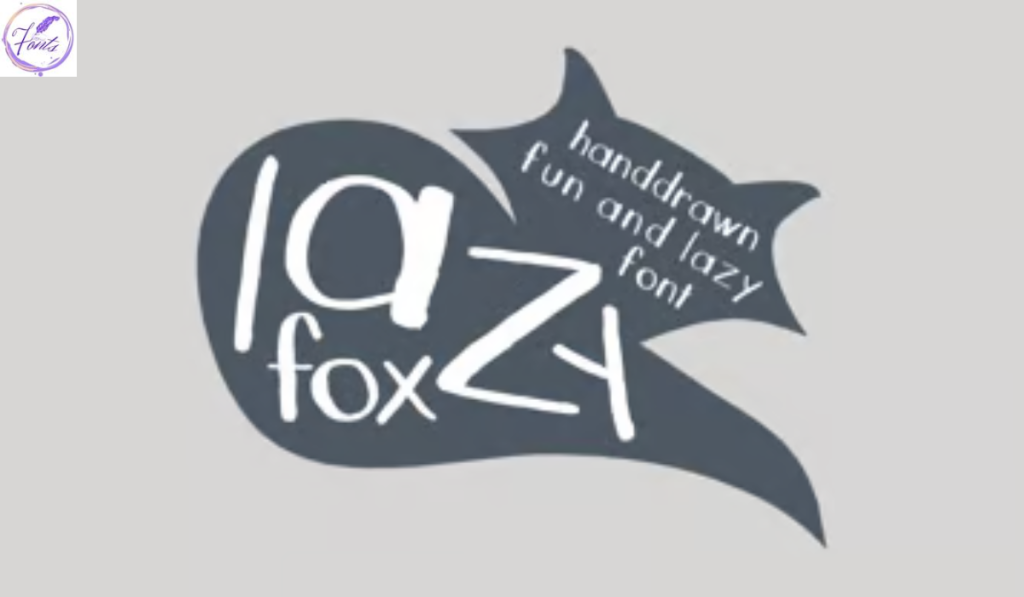
Font The Lazy Fox việt hóa
Tác giả: Jen Wicker
Ngày phát hành: 2019
Bộ Font: Lazy Fox
Phân loại: Cá tính, độc đáo
Kiểu chữ: Viết tay (handwritten)
Font The Lazy Fox là một kiểu chữ độc đáo và thú vị, ra mắt vào năm 2019 bởi Jen Wicker. Với những nét chữ mềm mại, thân thiện, và một chút nghịch ngợm, font the lazy fox mang đến cảm giác tươi mới và vui nhộn cho bất kỳ dự án thiết kế nào. Font này rất phù hợp cho các thiết kế thiệp mời, poster, và các ấn phẩm truyền thông cần sự thu hút và sinh động. Khả năng Việt hóa tuyệt vời của font này giúp người dùng dễ dàng sử dụng trong các văn bản tiếng Việt mà không gặp khó khăn gì.
Đánh giá font the lazy fox
Font The Lazy Fox đã nhận được nhiều lời khen ngợi từ cộng đồng thiết kế. Điểm mạnh của font này là sự kết hợp giữa nét chữ độc đáo và tính ứng dụng cao, tạo nên những thiết kế bắt mắt và thu hút. Khả năng Việt hóa của font the lazy fox cũng được đánh giá cao, giúp người dùng dễ dàng tích hợp vào các dự án tiếng Việt, đảm bảo tính thẩm mỹ và sự chuyên nghiệp. Nếu bạn đang tìm kiếm một font chữ vừa vui nhộn vừa dễ sử dụng, font the lazy fox chắc chắn là lựa chọn không thể bỏ qua.